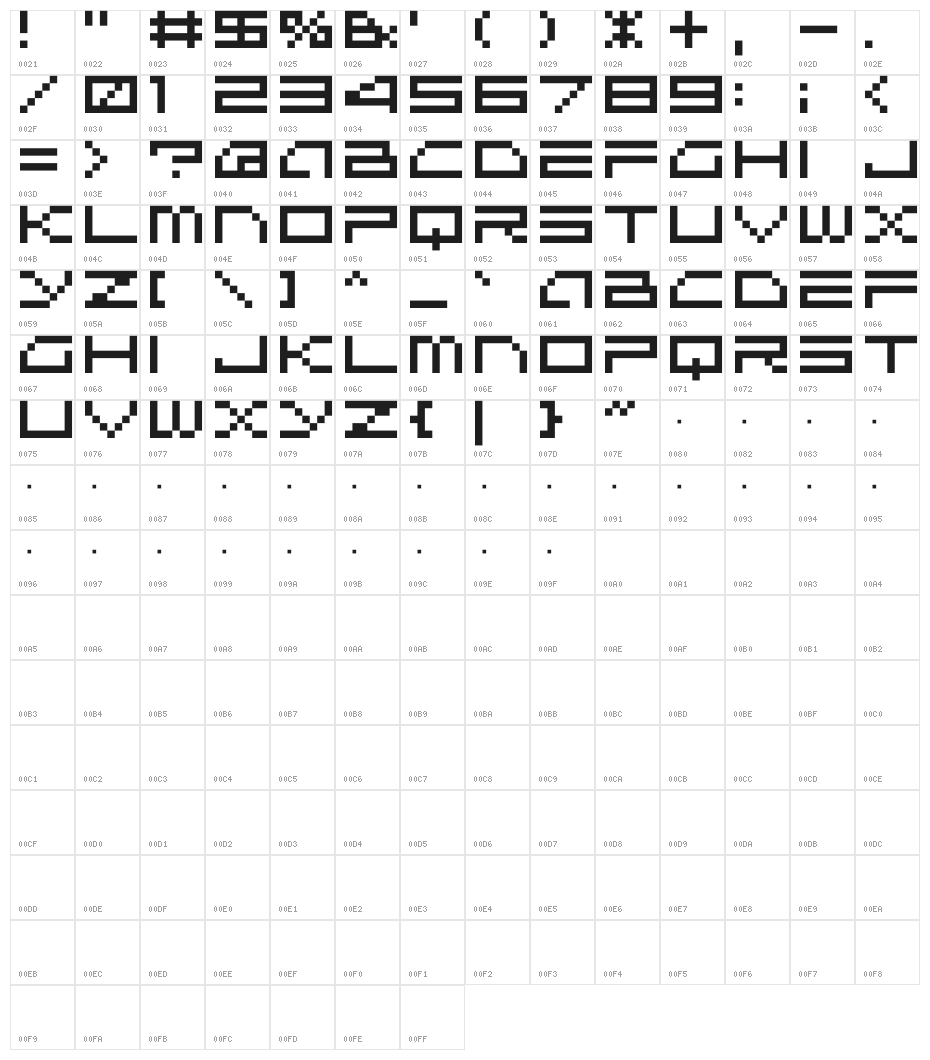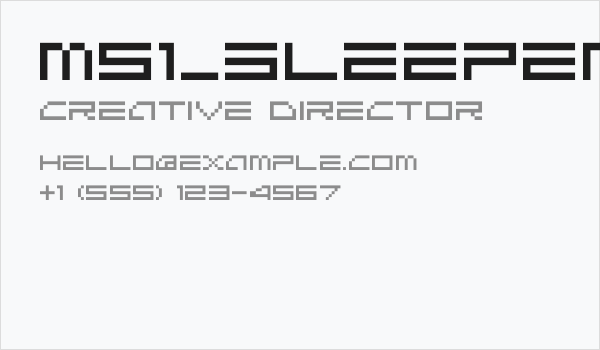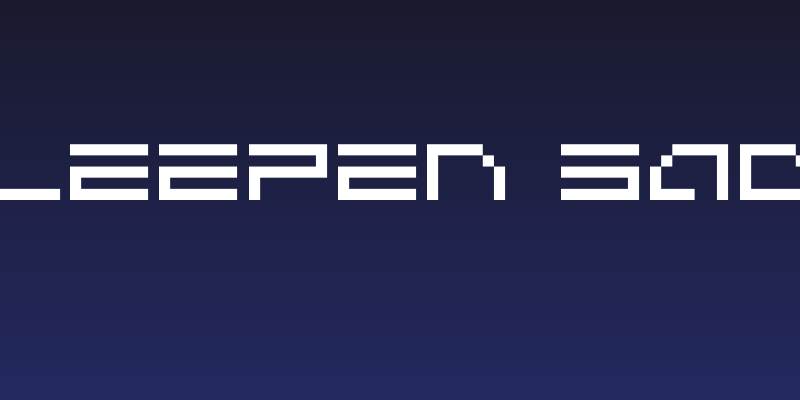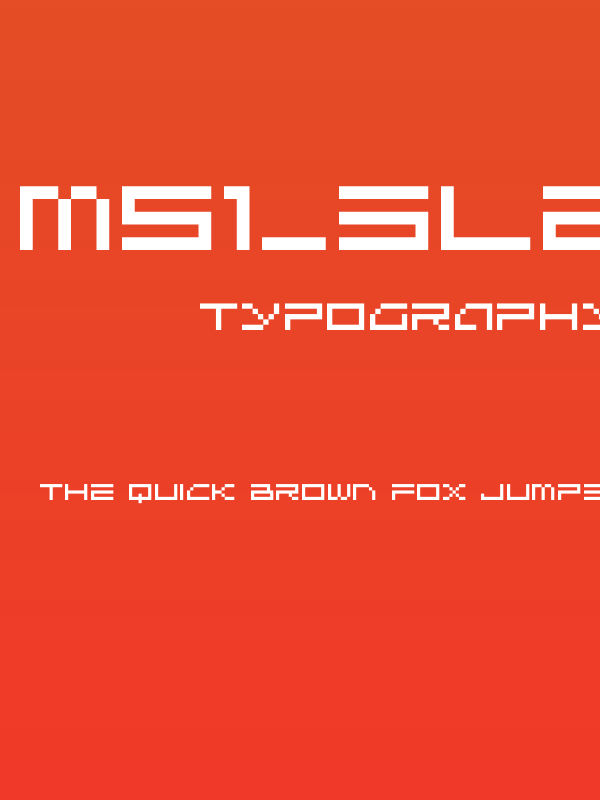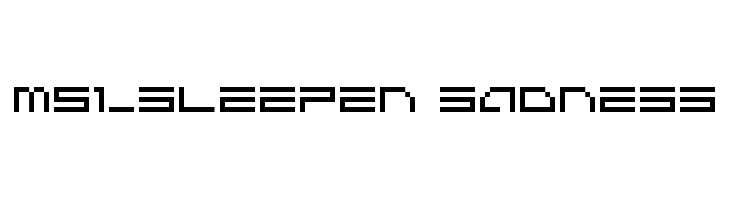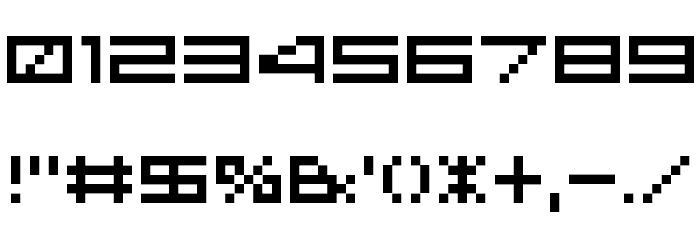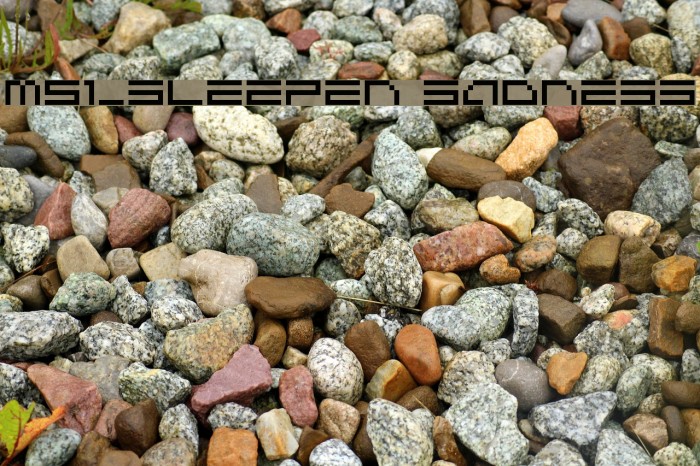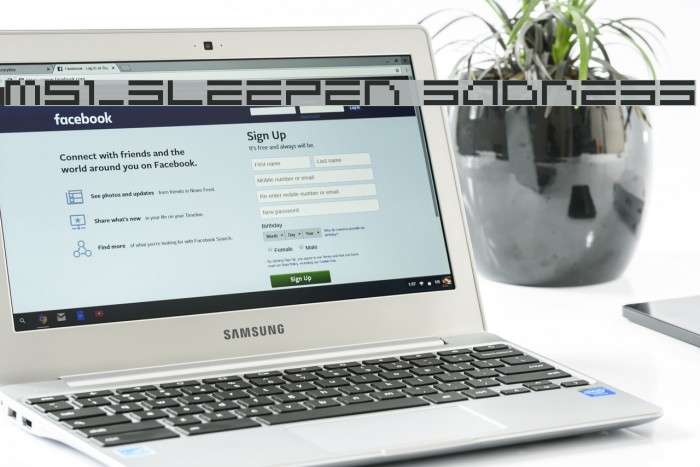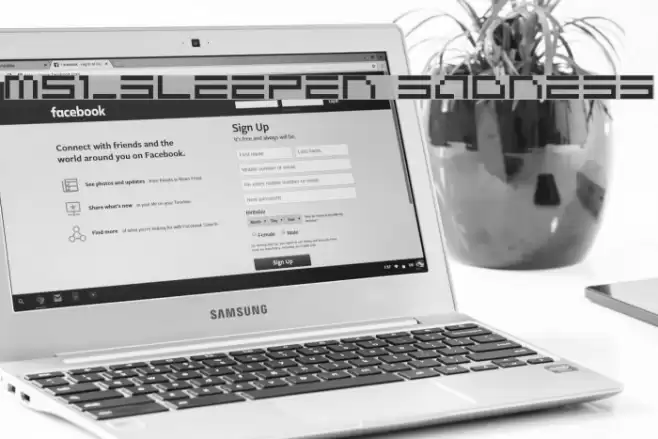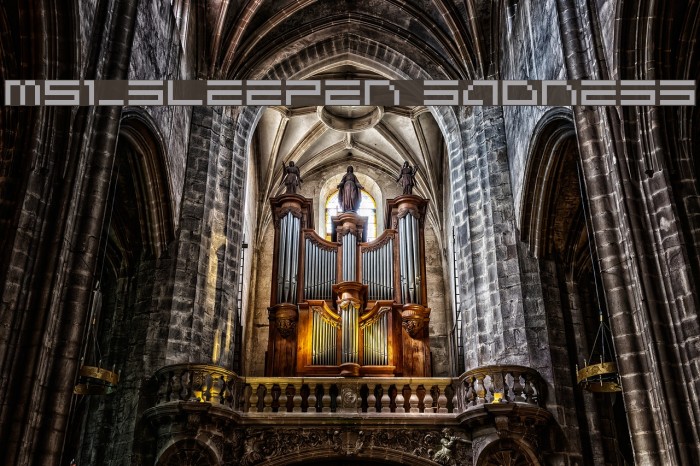
M51_SLEEPEN SADNESS Font
| Categorías | Pixel |
| Estilo general | Retro, Digital |
| Caso de uso | Logos, Posters, Digital Art |
| Proyectos propuestos | Ideal for video game design, tech-themed posters, digital art projects, and retro-style branding. |